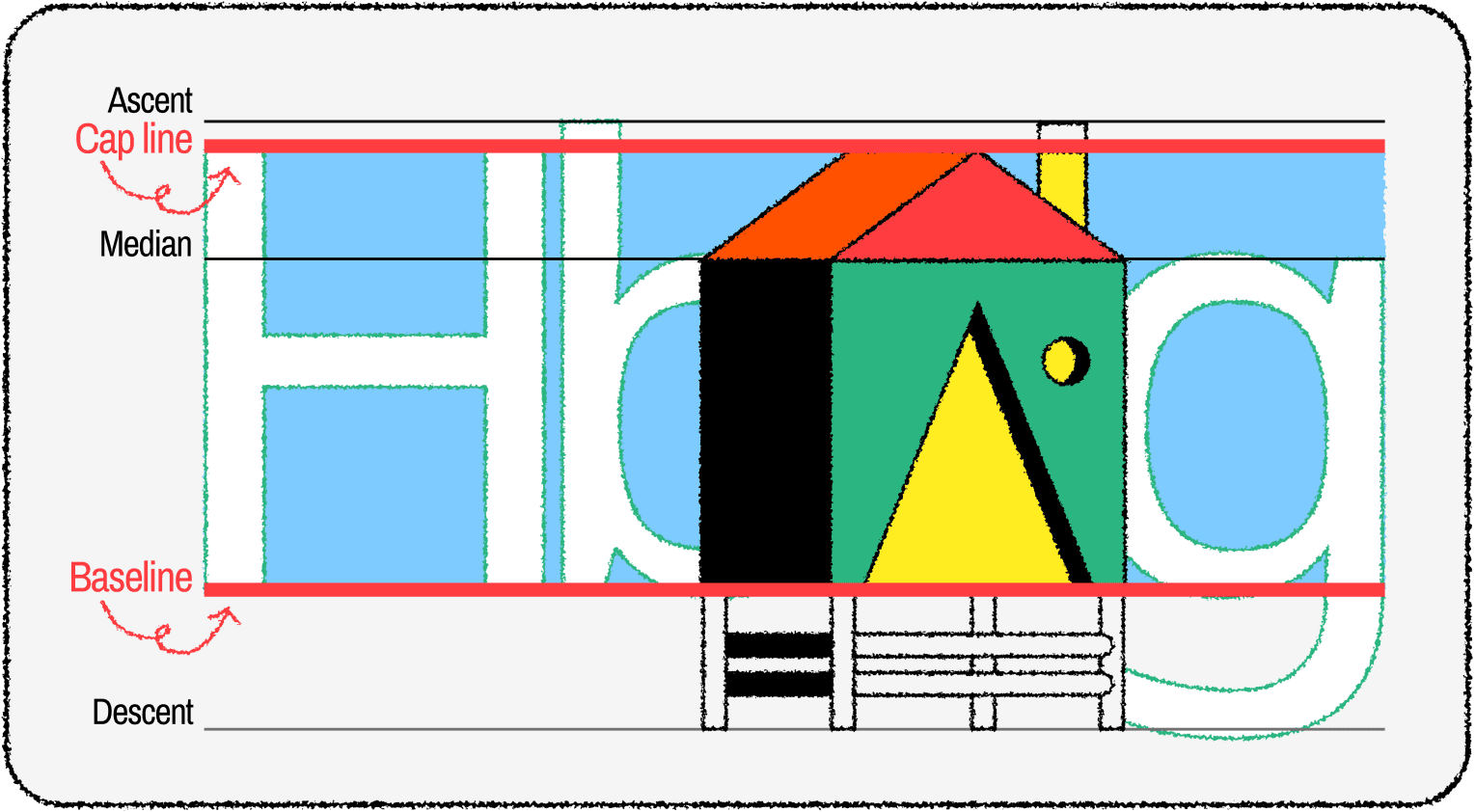
Đường ngang nằm bên trên baseline và nằm ở vị trí cuối cùng của các chữ hoa có phần đầu dạng bằng như chữ "H" được gọi là CAP LINE. Đường cap line cùng với baseline là 2 đường tham chiếu để xác định độ cao của chữ hoa (CAP HEIGHT) trong thiết kế chữ cái Latin. Đường cap line thường nằm bên dưới một đường tham chiều khác gọi là đường "ascent".